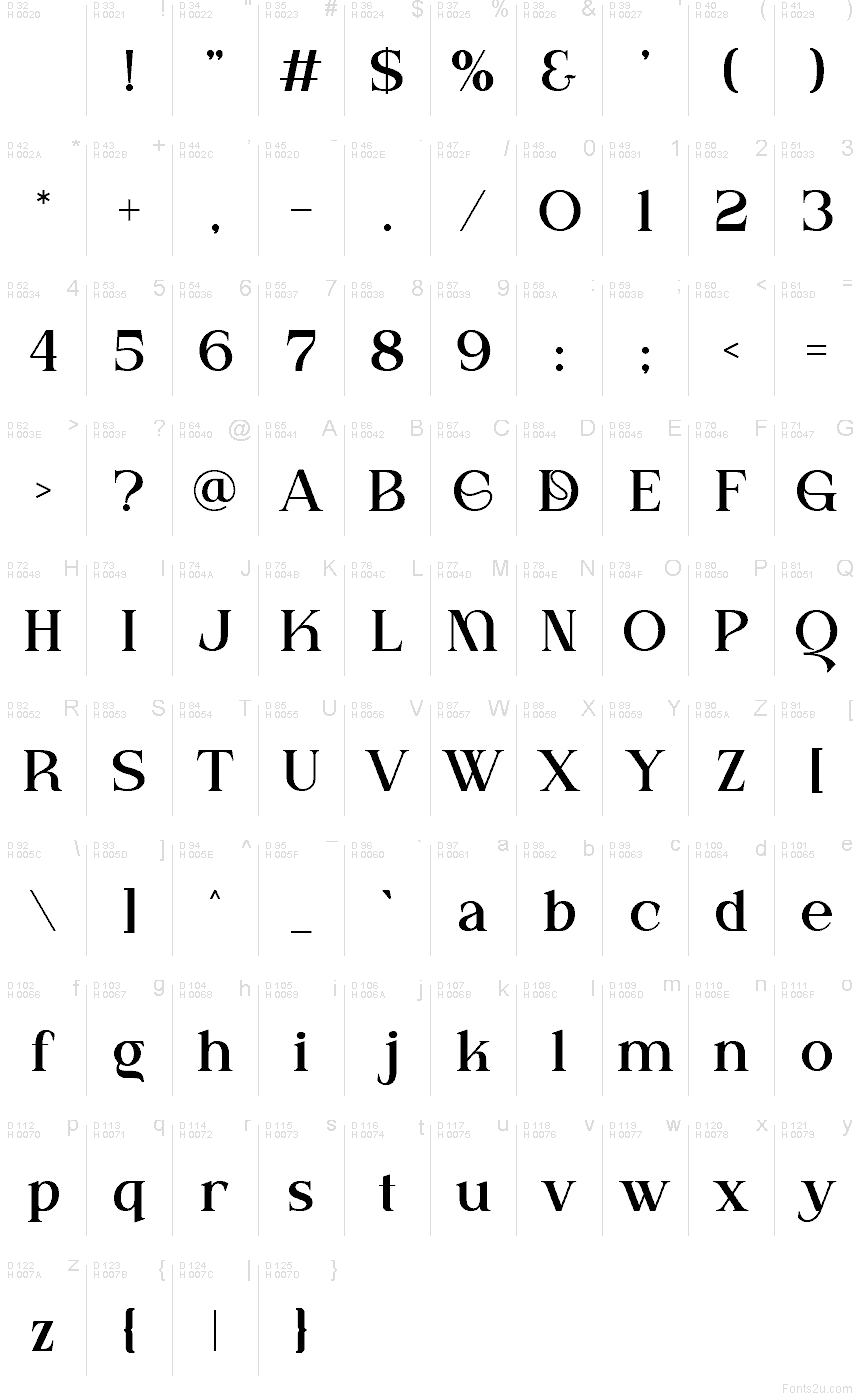
Makova autorstwa Ermedia Studio to darmowy krój szeryfowy o dużym kontraście, z szerokimi, nabrzmiałymi krzywiznami i wyjątkowo cienkimi liniami łączącymi. Jej wysokie, rzeźbiarskie litery wyglądają wdzięcznie, elegancko i lekko teatralnie.
W projektowaniu wydawniczym wyrazisty kontrast grubych i cienkich linii nadaje sesjom modowym, okładkom magazynów i dodatkom kulturalnym wielką dramatyczność klasycznej typografii akcydensowej. Te same zrównoważone kształty pasują do opakowań perfum i wizerunku butikowych marek, zwłaszcza w tematach związanych z haute couture, pięknem czy ręcznie wytwarzanym luksusowym rzemiosłem.